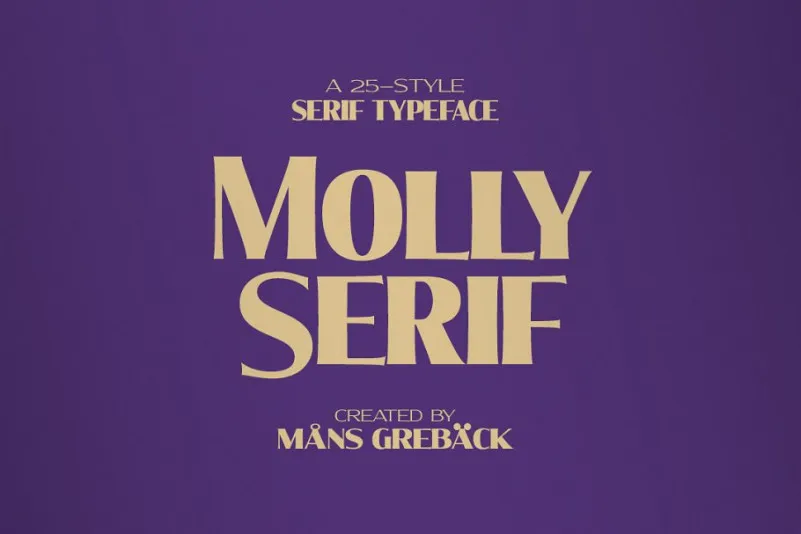
Molly Serif Font Family – Fonte Grátis
Molly Serif Font Family
Descubra uma nova fonte serif para suas criações no Brasil. Trata-se de Molly Serif Font Family, desenvolvida pelo talentoso designer Hamilton. Esta família de fontes conta com 25 estilos distintos, desde Extra-Condensed Thin até Extra-Expanded Black, criando flexibilidade e personalização sem igual. Com um estilo parecido à pintura em sinais tradicionais, esta face todo em letras maiúsculas se destaca em designs clássicos e genuínos. Suas características contrastantes e grande impacto podem ajudar a destacar seus logos e títulos na tela ou impressa. A Molly Serif é perfeita para criar headlines com uma aparência dramática, semelhante àqueles encontrados nos jornais ou em cabeçalhos de prêmio. Ela combina muito bem com estilos modernos e clássicos, tornando-se um recurso valioso para designers gráficos. A Molly Serif Font Family é uma escolha inteligente para quem procura uma fonte serif que não apenas atenda aos requisitos da legibilidade e profissionalismo, mas também oferece a potencialmente transformadora capacidade de destacar seu design em qualquer formato.